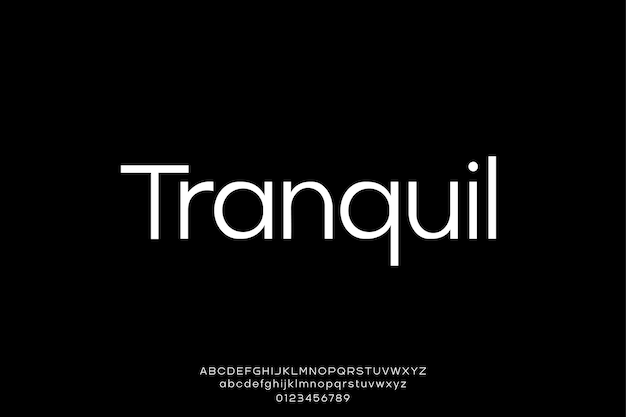
Polices abstraites de l'alphabet néon moderne. Conception arrondie de typographie pour le sport, le jeu, la technologie, la mode, le numérique, la future police de logo créative. illustration vectorielle